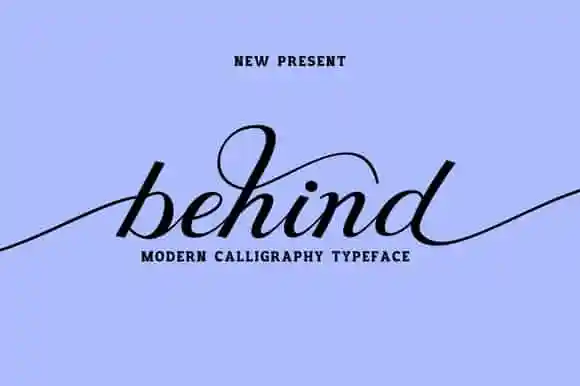
Behind Script Font – Download Grátis
Behind Script é uma fonte script escrita a mão que traz um toque suave de modernidade e fluididade, perfeita para projetos de design inovadores. Este conjunto de caracteres foi criado especificamente com versatilidade em mente, apto não apenas para títulos e logotipos, mas também para correspondências pessoais, convites de casamento, assinaturas, sinalização, rótulos, newsletters, outdoors, medalhas, camisetas, entre outros. Suavemente ondulado, a fonte Behind Script é uma opção ideal tanto para designers que buscam um charme simples e elegante quanto para aqueles que desejam inovar com elementos mais fluidos e suaves. Sujeitada à leitura rápida do olho humano, ela enriquece qualquer projeto com um toque de personalidade e sofisticação. Uma escolha perfeita tanto para projetos modernistas como clássicos, Behind Script é a fonte script escrita a mão que você precisa na sua próxima criação visual.